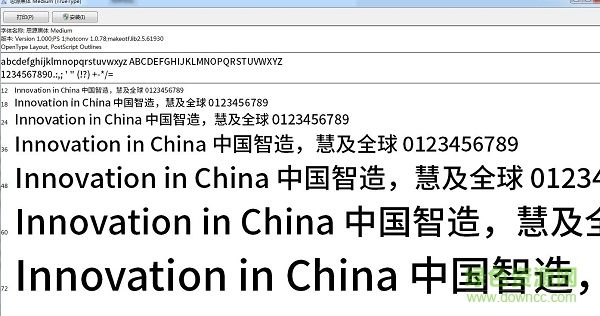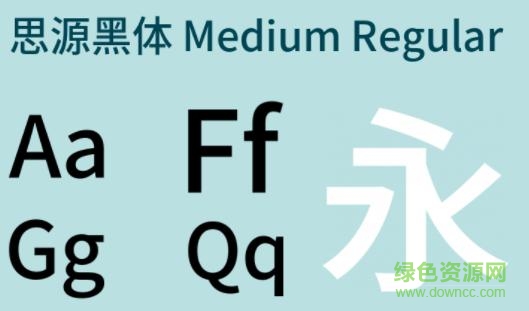
軟件介紹 軟件標簽: source字體 思源黑體 sourcehansanssc medium字體是一款粗細勻稱的tt體字體,結構嚴謹,清晰度高,表現力強,適合用在各種電子設備上,視覺效果不錯,需要更多思源黑體的朋友快來本站下載吧!思源黑體medium字體特征1.橫平豎直字見方,大小粗細一個樣;2.上緊下松要記牢 ,筆畫穿插又避讓;3.自隙均勻要講究,整齊美觀又大方。相關字體推薦思源黑體cn light 授權:免費軟件 WinAll, WinXP, Win7, Win8大?。?.8M語言:中文字體sourcehansanscn-light-gbpc-euc-h是一款ttf格式的高質量黑體字體,這款黑體的線條比較纖細,不僅適合平面設計、網頁設計等領域,也可以適當用在排版中,需要的小伙伴快來下載吧!黑體字體介紹無襯線體因其筆端方下載地址思源黑體cn medium-中(西方) 授權:免費軟件 WinAll, WinXP, Win7, Win8大?。?.9M語言:中文sourcehansanscnmediumgbpceuch字體又叫思源黑體cnmedium-中,是一款由Adobe公司開發(fā)的黑體字體,同時支持中英文顯示,粗細勻稱,轉角處理精致,需要的朋友快來下載吧!黑體字體介紹“黑體”是一類字體的總稱,有很多下載地址sourcehansanssc字體安裝方法1.在綠色資源網下載字體包,并解壓縮2.最簡單的安裝方法:雙擊字體文件,點擊安裝按鈕即可3.批量安裝方法:將字體文件放到C:\Windows\Fonts 軟件截圖 上一張下一張(1 / 1) 安裝詳細截圖 其他版本下載 標題 大小 更新日期 下載 思源黑體(Source Han Sans) 開源字體_中日韓專用 46.96M 2014-12-23 下載 思源黑體cn bold粗體 7.19M 2017-05-16 下載 思源黑體中文官方 最新版(22款) 139.00M 2019-12-18 下載 思源黑體cn medium-中(西方) 4.88M 2018-05-30 下載 思源黑體cn light 6.83M 2017-11-09 下載 思源黑體 cn normal-亮體字體 .ttf 14.64M 2018-05-30 下載 sourcehansanscn extralight 6.05M 2017-12-13 下載 思源黑體bold字體 12.69M 2018-06-06 下載 思源黑體normal字體 13.67M 2018-06-06 下載 思源黑體臺灣版(Source Han Sans TWHK) 31.67M 2019-02-16 下載 下載地址 電腦版 思源黑體medium 中ttf 點擊報錯 軟件無法下載或下載后無法使用,請點擊報錯,謝謝! 關閉報錯反饋 請描述您所遇到的錯誤,我們將盡快予以修正,謝謝! *必填項,請輸入內容 本類最新 dreamweaver字體庫 首爾南山體字體 v1.06 官方版 潮字社風云簡ttf 潮字社凌渡鯤鵬簡體字體 潮字社曾玉波手書簡字體 微博慧心字體 相關文章 解決HD Audio驅動安裝失敗的問題 Eisoo DiskGenius恢復無法訪問的移動硬盤數據 開機就顯示:Disk Boot Failure,Insert System Disk And Press Enter 教你克服DIY裝機五大誤區(qū) 錯誤 2812: 未能找到存儲過程 'master.dbo.xp_fixeddrives' div+css下js浮動對聯(lián)廣告不隨屏幕滾動的解決方法 用戶評論 熱門評論 最新評論 發(fā)表評論 查看所有評論(0) 昵稱: 請不要評論無意義或臟話,我們所有評論會有人工審核. 字數: 0/500 (您的評論需要經過審核才能顯示)